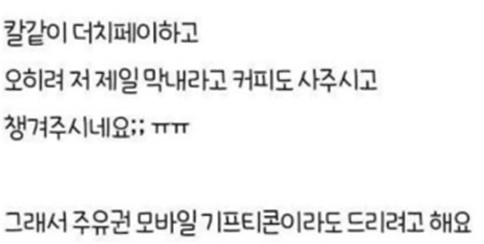
글씨체 궁금해요
ㄸ과 ㅍ 그리고 ;; 이 포인트인 글씨고
전체적으로 글씨체 크기는 비슷한것같아요
ㄸ과 ㅍ 그리고 ;; 이 포인트인 글씨고
전체적으로 글씨체 크기는 비슷한것같아요
Na 완전됴하영 입니다. https://galaxystore.samsung.com/detail/com.monotype.android.font.naverygoodk?session_id=W_0f87e9a2bfb0319215a7a379c36f7f4c